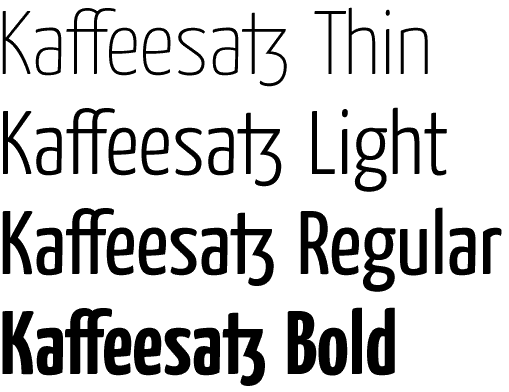
Best of... 2006As melhores fontes de 2006 são...»» Categoria "Internacional": Darka, de Gabriel Martinez MeaveO tema das Blackletter mexicanas foi bastante comentado em 2006. Boa razão para seleccionar este belo desenho que não é alemão!
Gabriel Martinez Meave foi um dos Winner of the 2006 Type Directors Club Type Design Competition. Os seus outros desenhos de letra estão em www.kimera.com.mx/tipogaleria.html »» Categoria "Lusitanas": Andrade, de Dino dos SantosNa jovem cena do typeface design português, não são apresentados muitos novos desenhos no decorrrer de um ano. Em 2006, não houve dúvida: Um desenho brilhante é a Andrade Pro, de Dino dos Santos. Os cortes Swash são ... uma jóia da Calligraphia Portugueza. Veja a fonte em www.dstype.com
Dino dos Santos ¦ O Senhor Manuel de Andrade de Figueiredo »» Categoria "originalidade": Superveloz
»» Categoria "Freefont": Kaffeesatz de Yannone
»» Categoria "universalidade": Gentium de Victor Gaultney
Gentium a typeface for the nations pode ser baixada em scripts.sil.org. esta família de fontes é um verdadeiro benefício para a Humanidade (não estou a exagerear!) Foi desenhada por Victor Gaultney no âmbito do seu Mestrado em Typeface Design na University of Reading. Temas relacionadosTDC Annual Awards 2006, Grand Prix : Hideki Nakajima http://www.tdctokyo.org/awards/ |